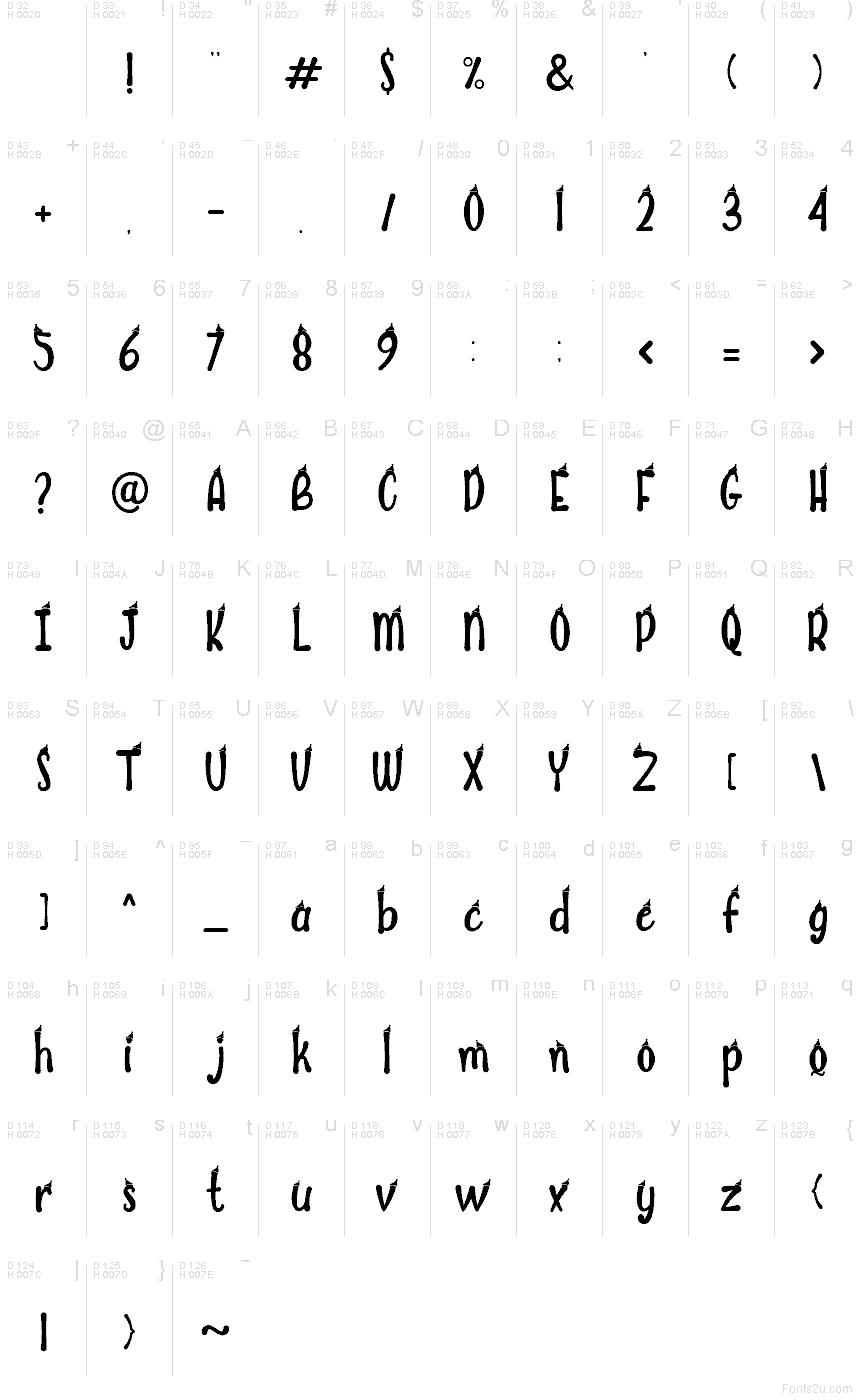
Cute Snow Santa Hat od Putracetol Studio je bezplatné vánoční písmo typu script, které přináší veselou sváteční náladu. Písmena mají hladký, štětcový tah a lehce poskakující rytmus. Drobné čepičky Santa Clause usazené na znacích proměňují celý design ve sváteční nápis, který vypadá mnohem zajímavěji než běžné ručně psané písmo.
Skvěle funguje na sezónních přáních, jmenovkách na dárky, pozvánkách, obalech na pečivo i příspěvcích na sociálních sítích, kde samotné písmo nese hlavní téma. Jako bezplatný font se hodí také pro krátké nadpisy, tabule s nabídkou nebo vánoční akční bannery, protože motiv čepičky dodává i jednoduchým slovům nezaměnitelný vánoční nádech.